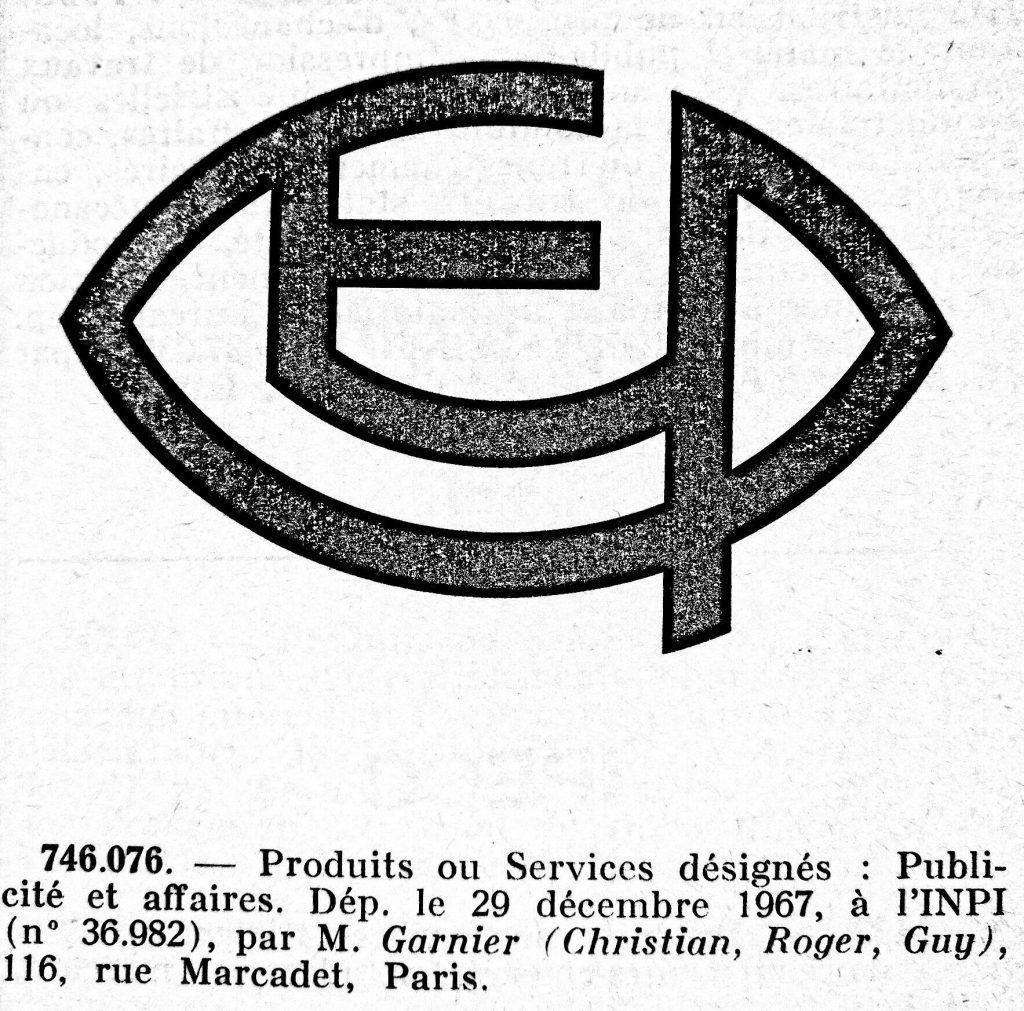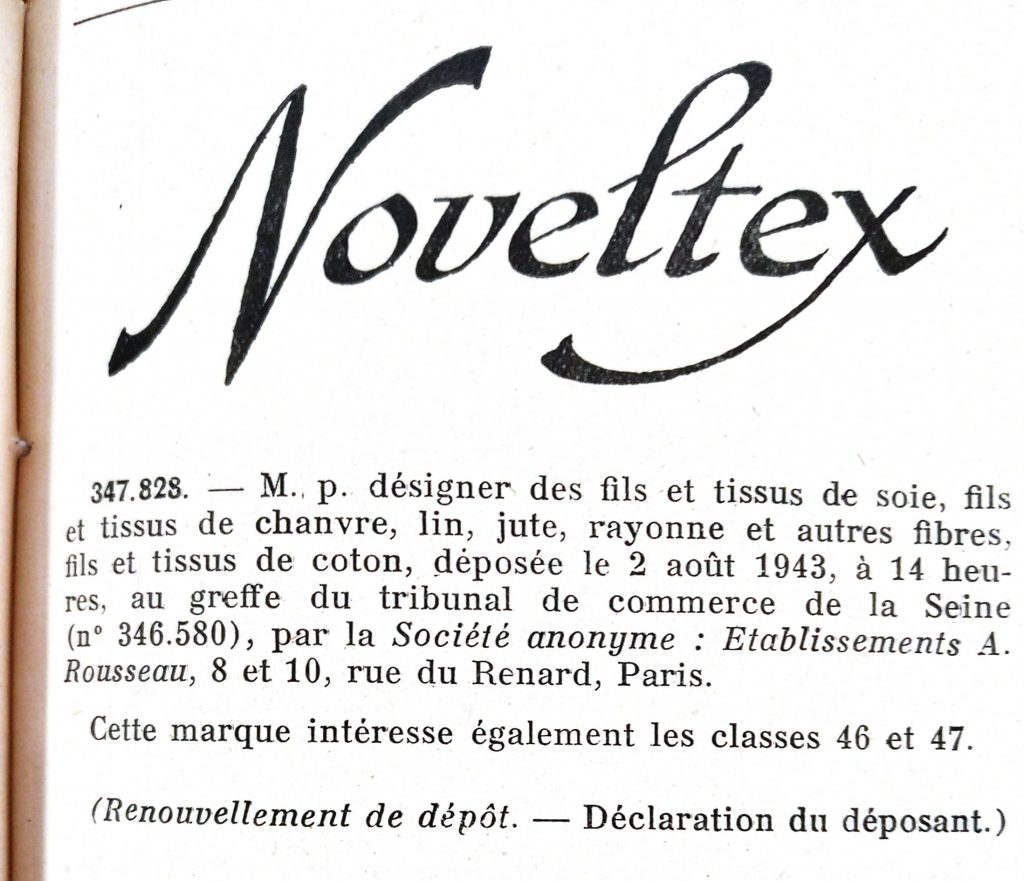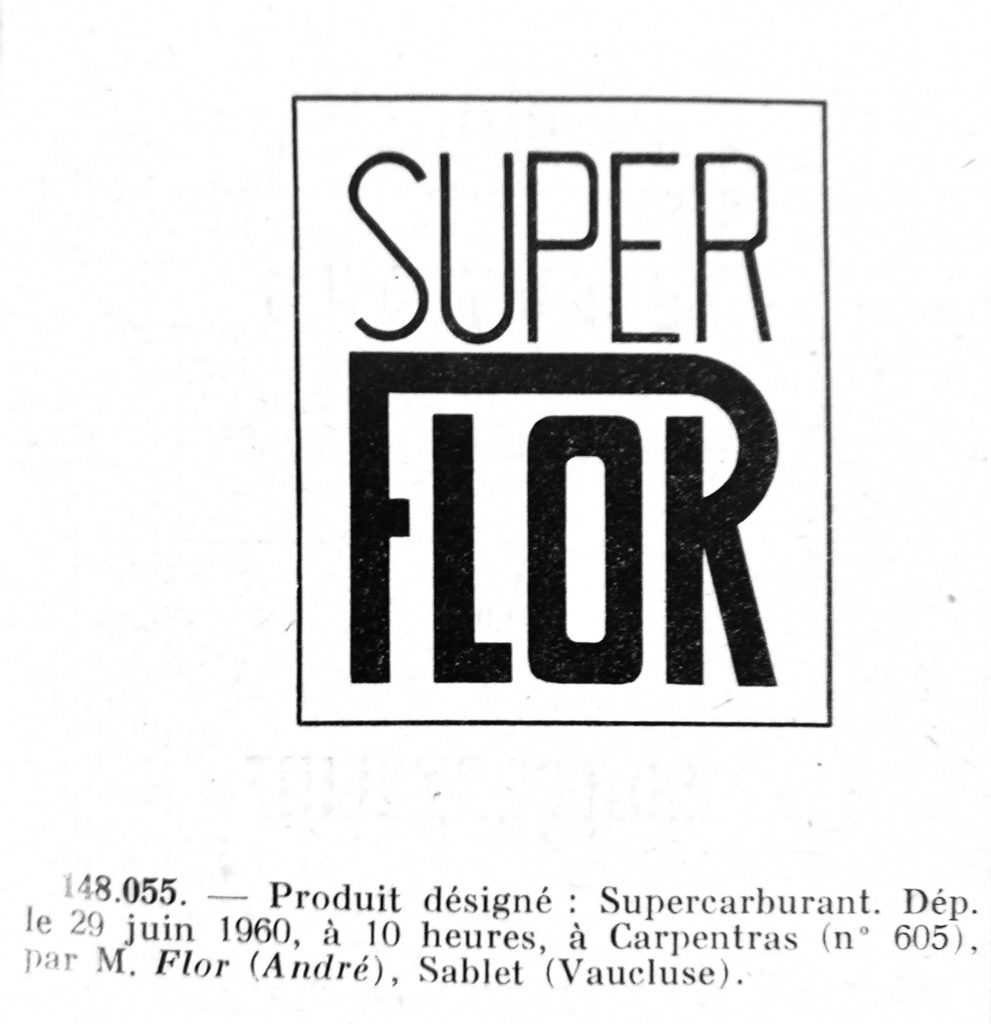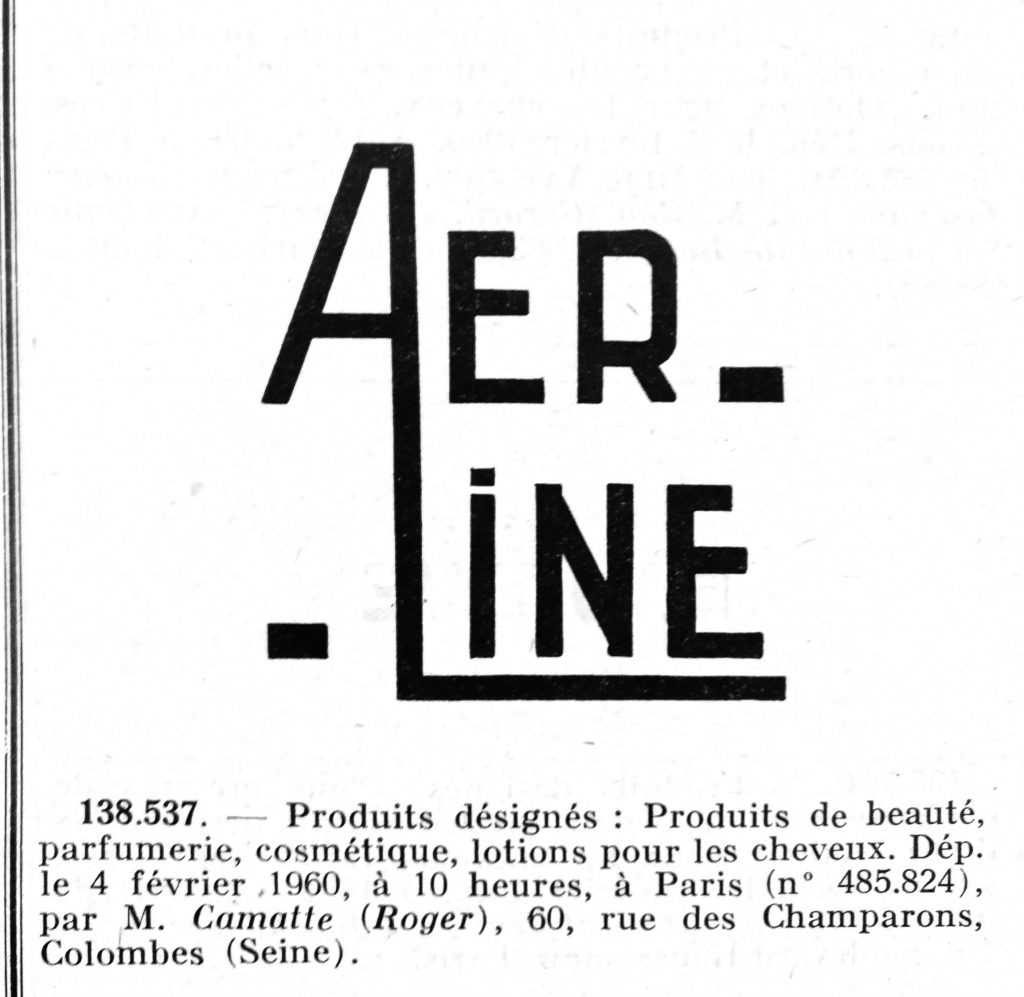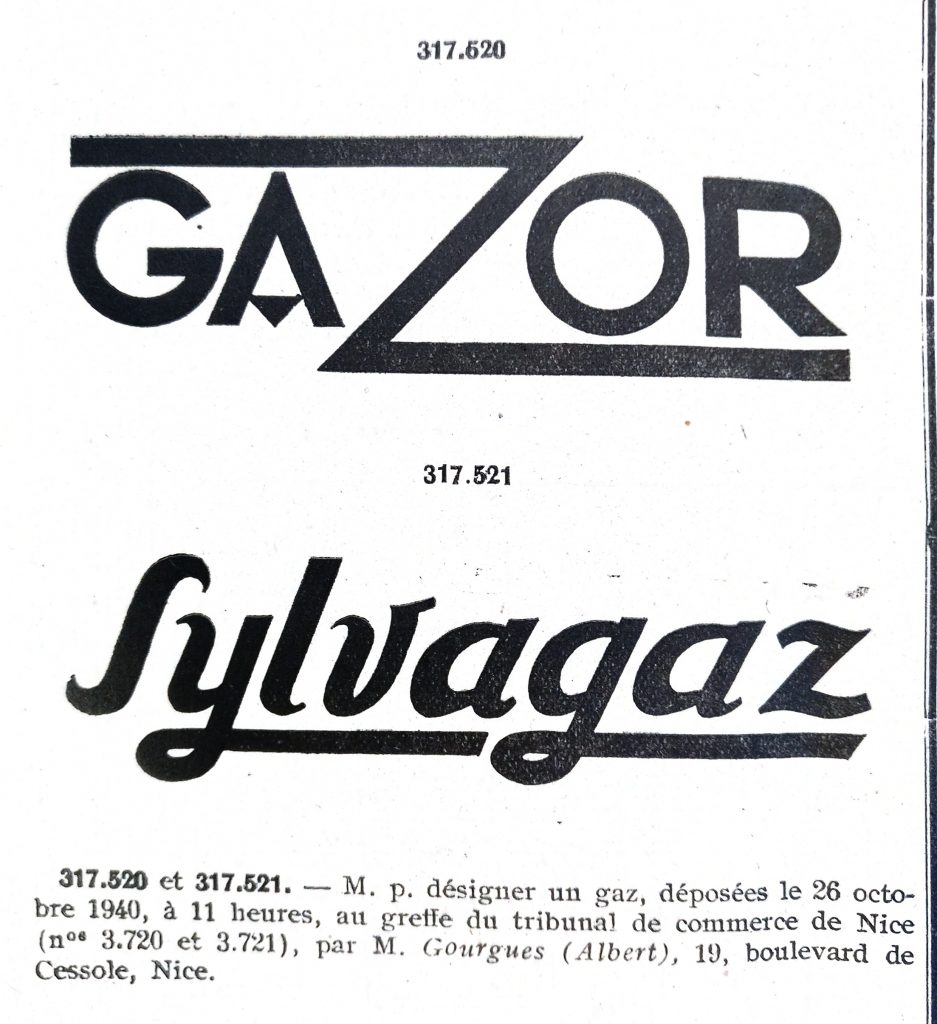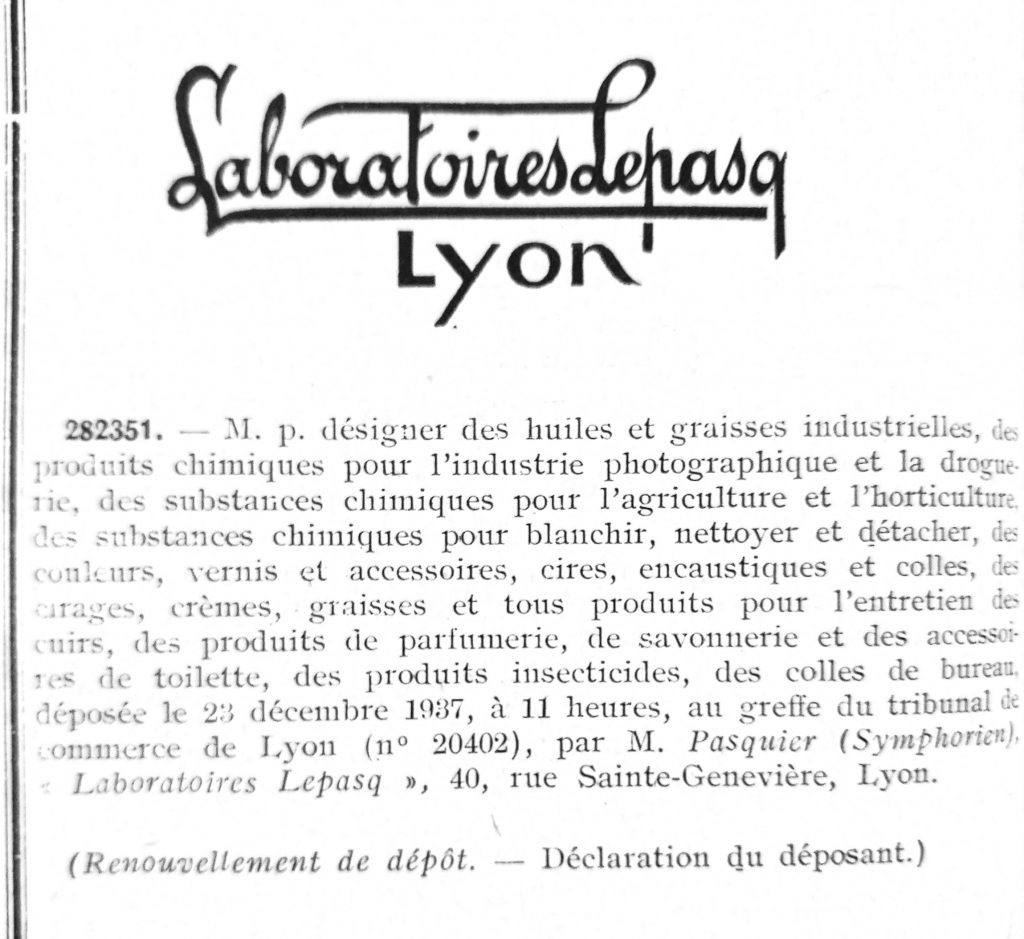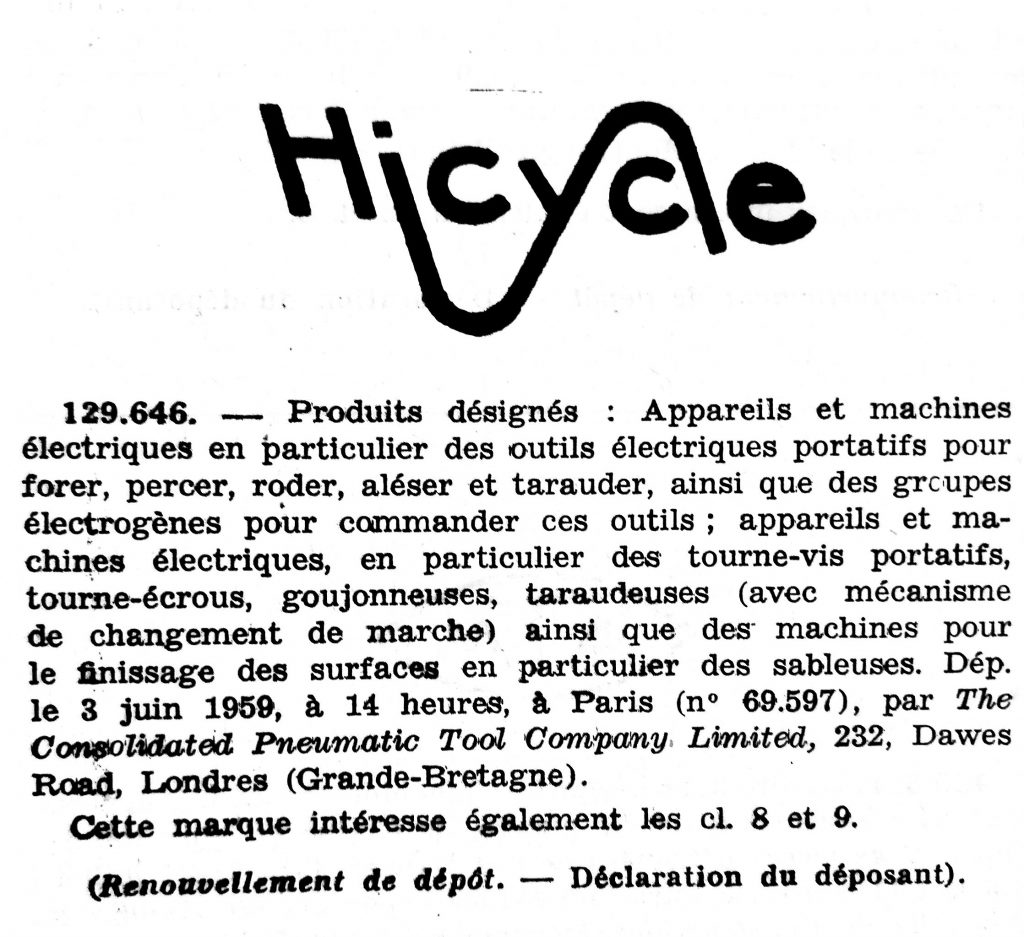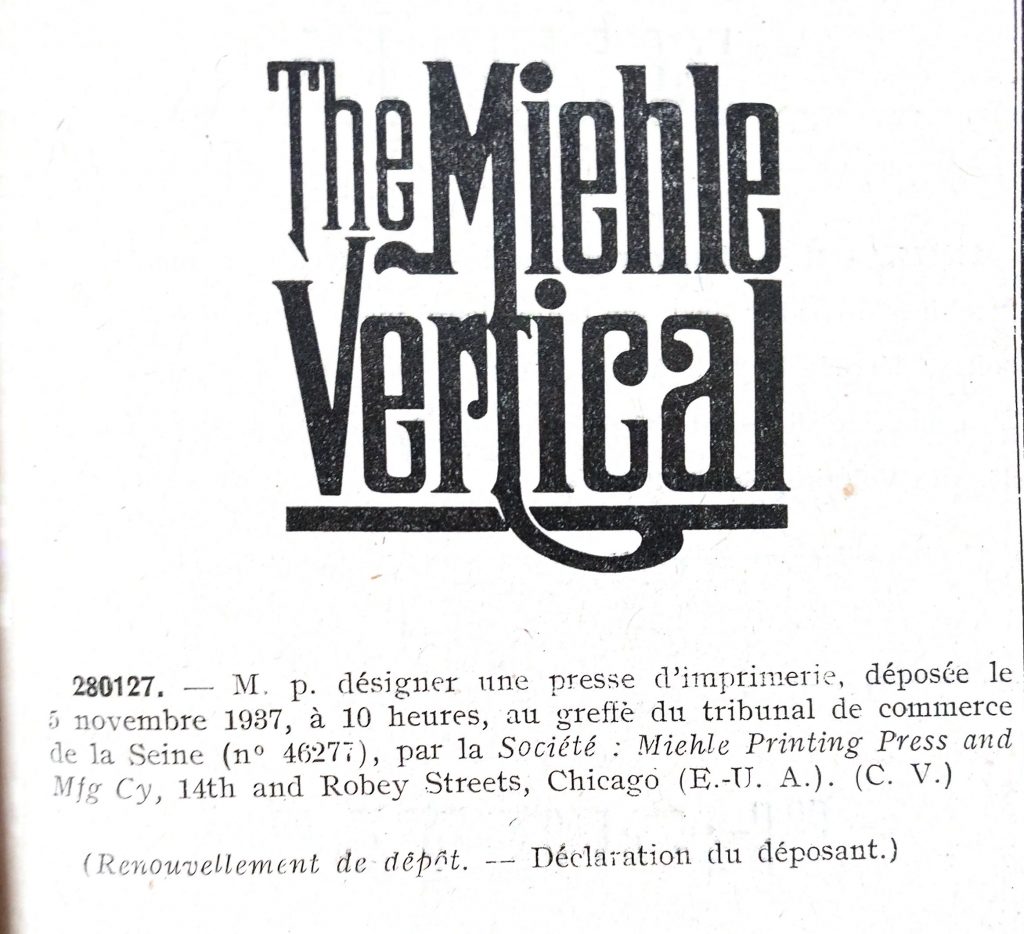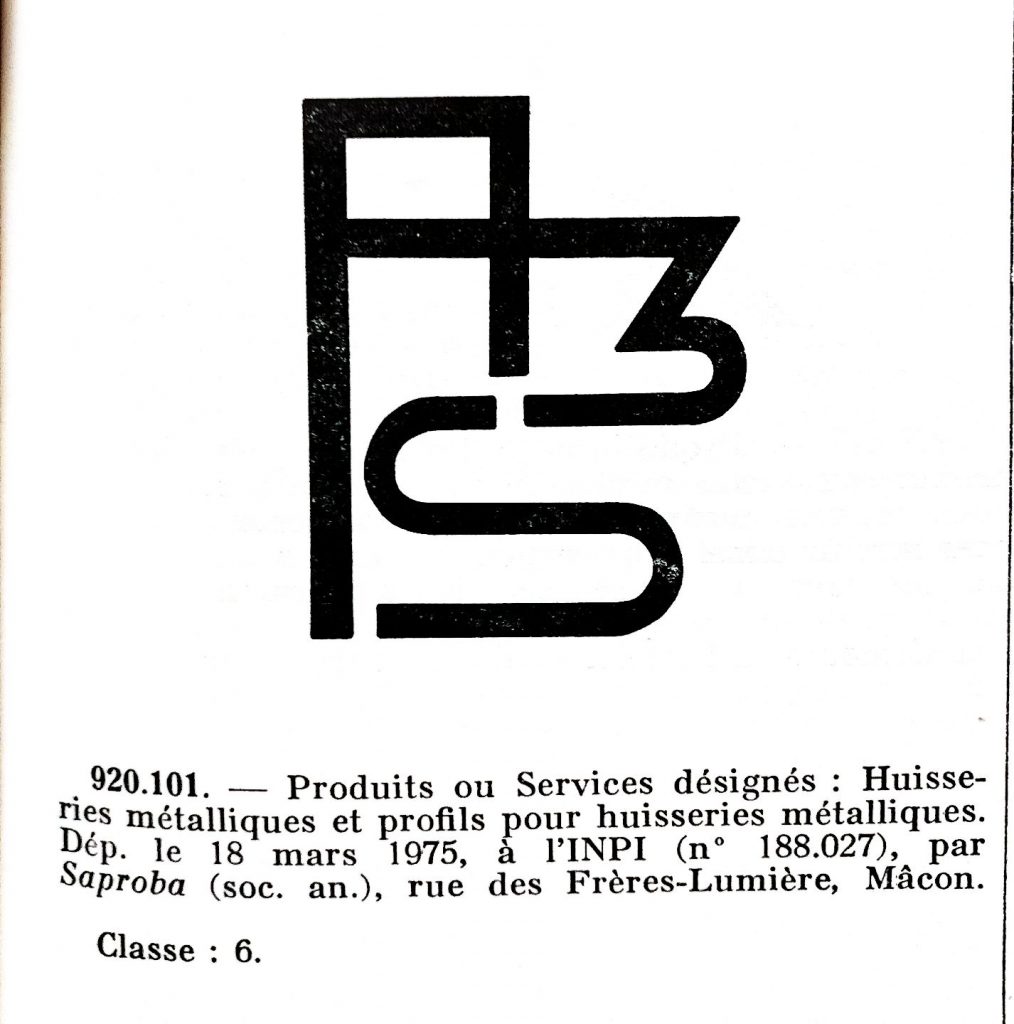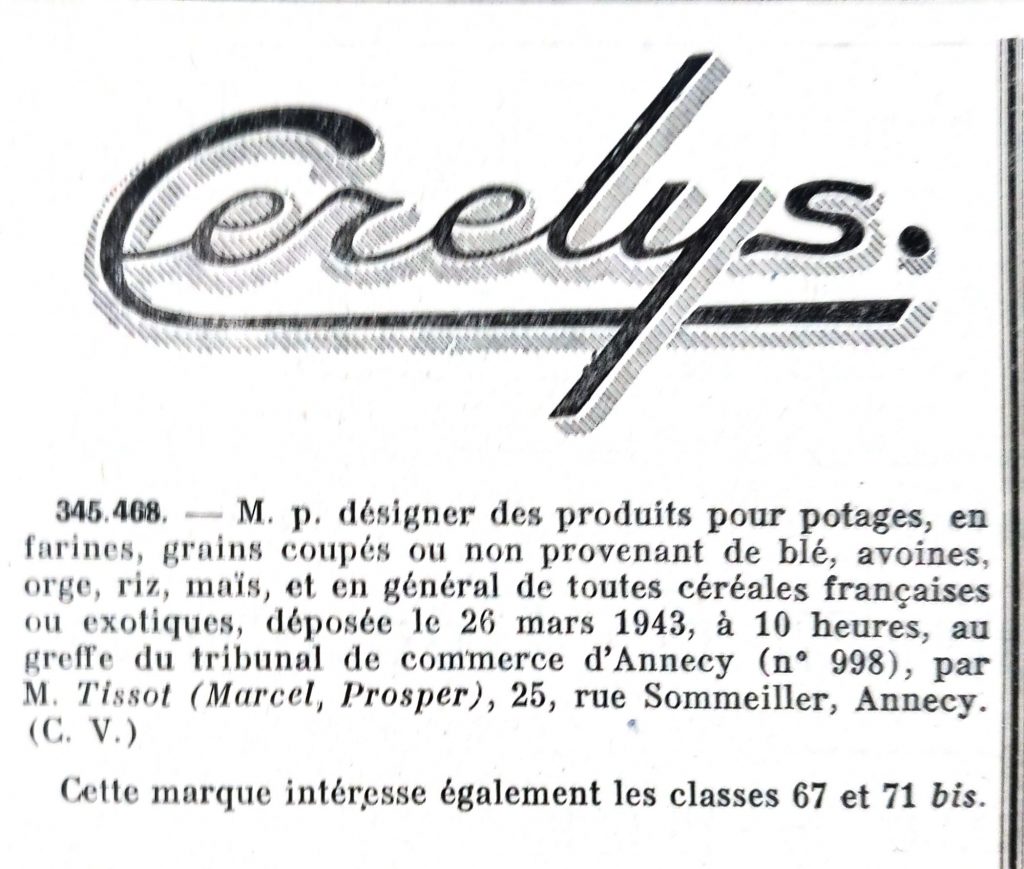
Typographie : prolongements et ligatures
Dans toutes les marques rassemblées ici, il est une ou plusieurs lettres dont le graphisme s’étend au delà des limites habituelles de façon à former une calligraphie particulière.
Avec ces prolongements de lignes, il s’agit souvent de souligner [à l’instar de marques publiées dans la série « l’art de bien souligner », épisode 1 et épisode 2], de surligner, d’entourer et parfois de relier.
Lorsque des lettres sont reliées entre elles, cela pourrait correspondre à ce que les typographes considèrent comme une ligature, c’est-à-dire la fusion de deux ou trois graphèmes pour en former un nouveau.
Mais dans les cas de caractères reliés suivants, les lettres ainsi jointes ne sont pas contigües. cela rend l’aspect de ces marques semi-figuratives d’autant plus singulier.